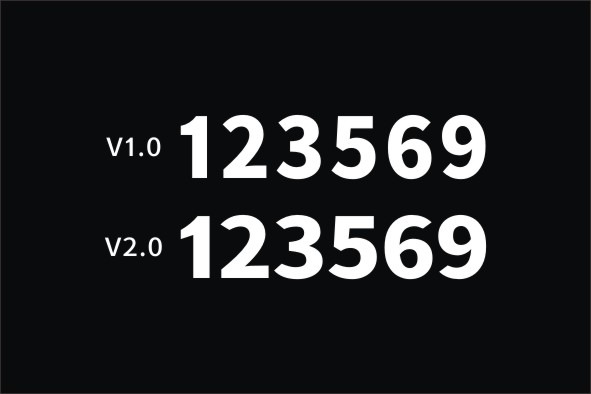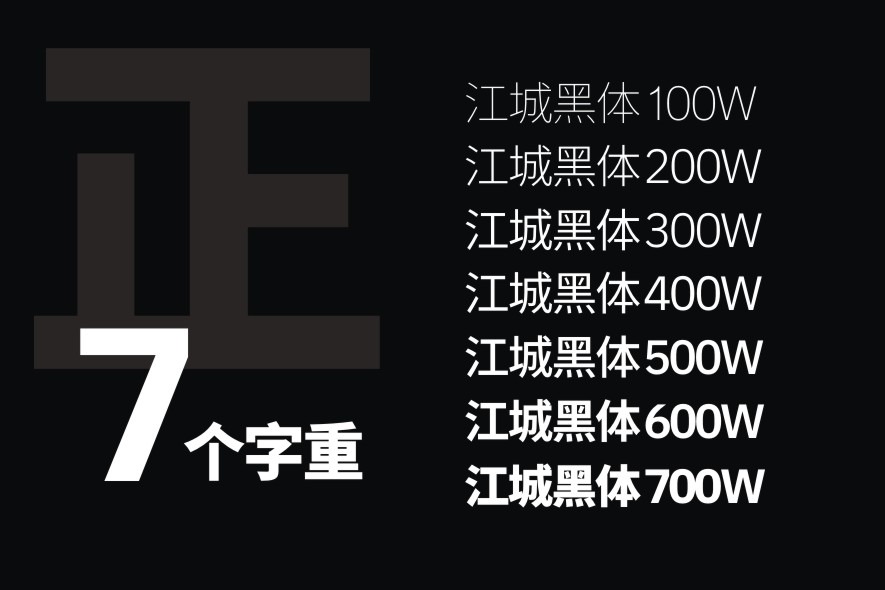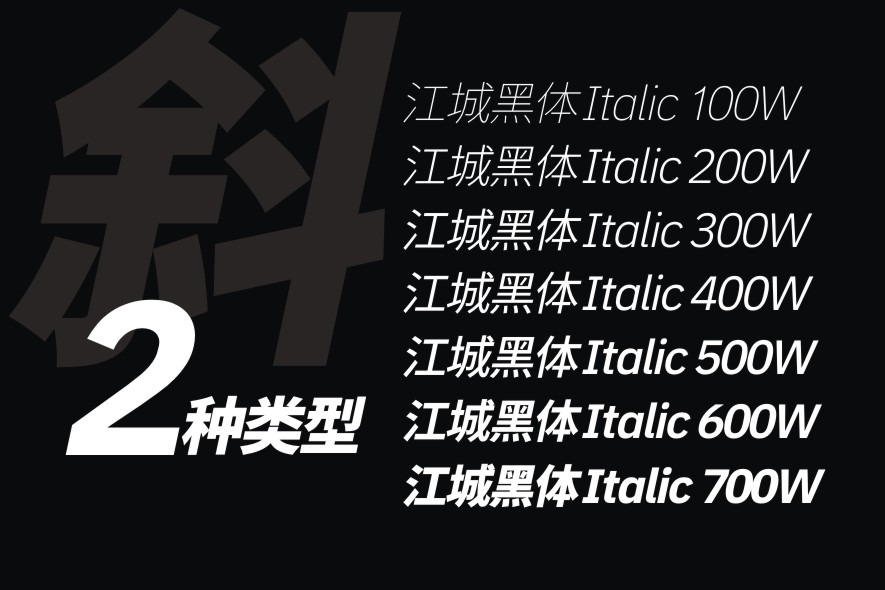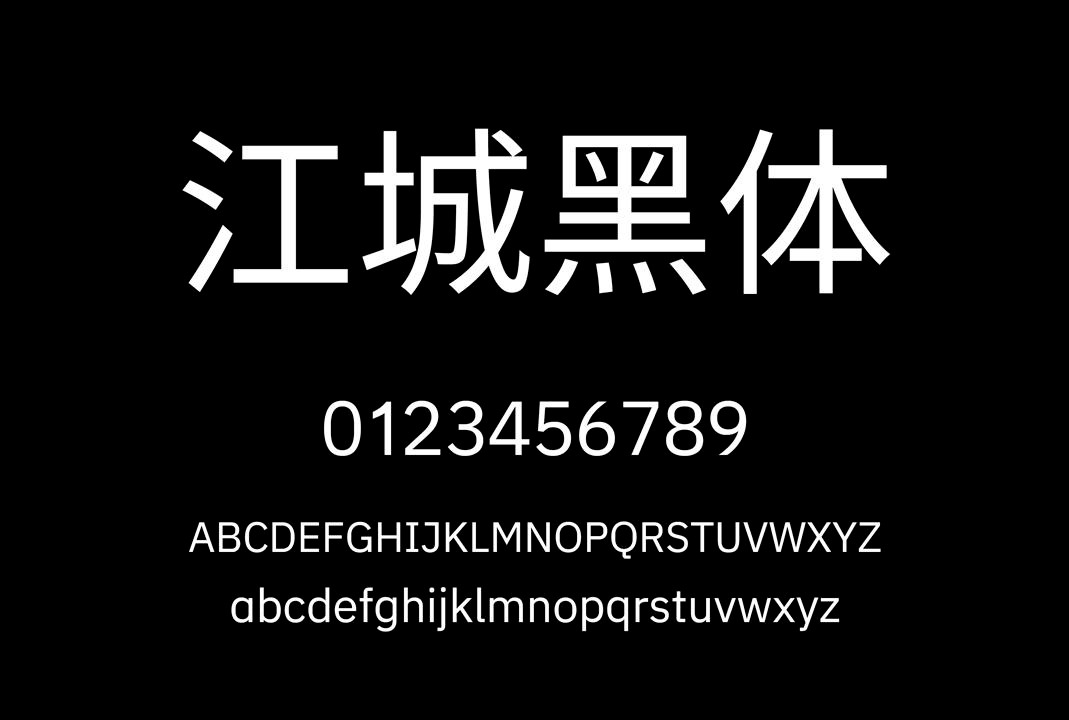
江城黑体是一款由刘鹏(@设裂星辰)基于思源黑体改造优化的免费可商用中文字体,主要优化了其中的数字字形。
作者发现,带有下面横线的数字“1”非常适合屏幕显示,但并不适合物料印刷等材质上的呈现。于是就去掉了数字“1”下面的横线,并着重优化了数字的重心平衡和间隔空隙,使排版更美观。同时,调整了字符范围,使得江城黑体在PS、AI等软件中显示在中文区,更方便设计师寻找和使用。
江城黑体覆盖简体中文、繁体中文、常用日文、韩文、拉丁字母、符号,共约 3 万字符。提供 7 种标准字重(100W-700W)和配套的斜体,可以满足从正文到大标题的全场景需求,